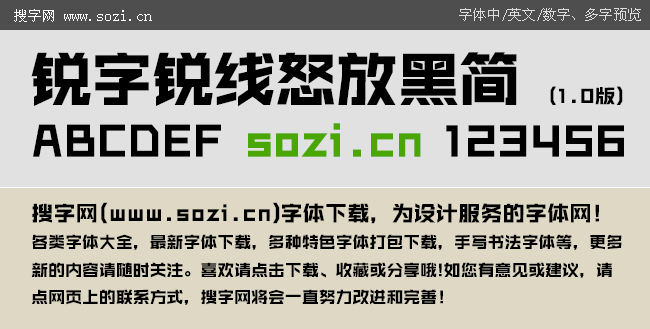
銳字銳線怒放黑簡1.0
搜字網(wǎng)提供一款銳字銳線怒放黑簡1.0中文字體下載,銳字銳線怒放黑是一款以黑體字為原型,進(jìn)行了新的藝術(shù)設(shè)計的藝術(shù)字體,適合應(yīng)用于廣告設(shè)計、名片設(shè)計、包裝印刷、產(chǎn)品設(shè)計等應(yīng)用。